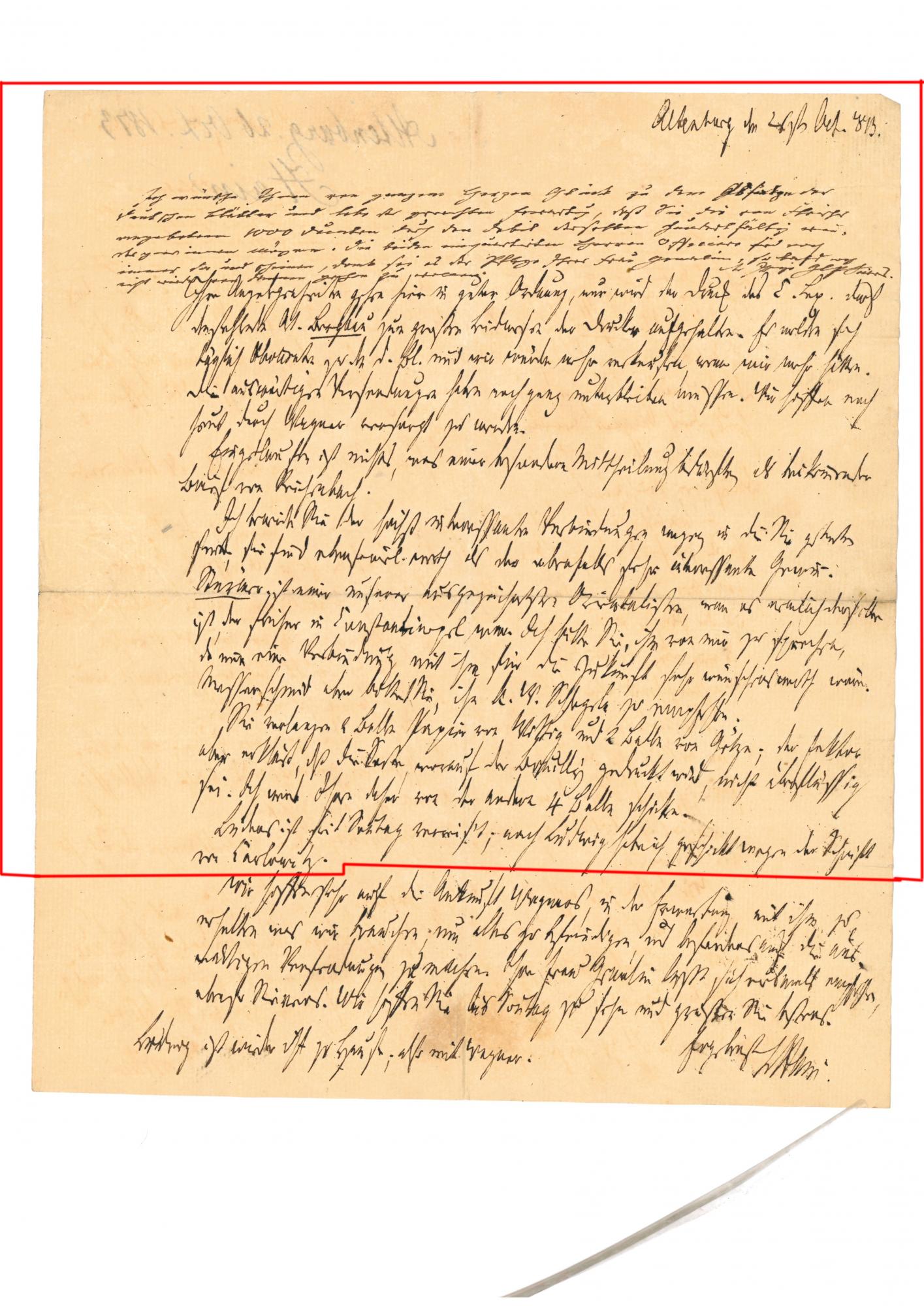
Brief Hain an Brockhaus/ Übersetzung
ich würde gerne diesen Brief transkribieren und komme leider nicht weiter. Den ersten Absatz habe ich schon, allerdings brauche ich nun Hilfe. Vielleicht kann mir einer helfen.
Der Brief ist von 1813 und ist im Anhang.
Hier treiben sich mämlich Leute herum, die allein schon aus Interesse extrem viel Erfahrung mit Kurrentschriften haben, und so was dann locker herunter lesen, während die meisten von uns eher wenig Kontakt zu solchen Dokumenten mit deutlich "ausgeschriebener" Handschrift haben, die sich selbst dnn für außenstehende kaum lesen lässt, wurde lateinische Schreibschrift verwendet.
Wozu brauchst Du denn die Transkription? Scheint ja ein interessantes Projekt zu sein! (Tante Edit ergänzt: Der Dateiname weist darauf hin, dass das Bild für das Hochladen bei Moodle vorgesehen ist, einer Lernplattform für Universitäten, auf der Dozenten Arbeitsaufträge und Informationen bereitstellen können... Irgendwo scheint es an einer Uni ein (Pro-)Seminar zur Edition von Briefen o.ä. zu geben. Doch nicht etwa bei Dr. Strobel, meinem alten Dozenten und Prüfer im Magisterexamen?)
Ja genau es handelt sich um ein Proseminar, wir haben auch schon einige Briefe übersetzt, aber bei dem hier weiß ich leider nicht weiter und kann so gut wir gar nichts entziffern.. Vielen Dank ich schaue dort einmal!
Eigentlich finde ich es ja besser, wenn man sich durch solche Aufgaben durchbeißt: Wenn man einen solchen Text erst einmal bezwungen hat, ist das ein großes Erfolgserlebnis, und man hat auch wirklich was gelernt; das habe ich während meines Studiums oft erfahren dürfen. Die Edition kann Dir natürlich, falls Du Dich irgendwo festgefahren hast, auf die Sprünge helfen und Dir als Schlüssel für schwer lesbare Buchstabenformen dienen. Ich rate Dir aber, sie wirklich nur als Anschub zu benutzen und möglichst viel selbst zu machen. Bei Stockungen wirkt es übrigens meist Wunder, die Arbeit beiseitezulegen und am nächsten Tag noch einmal mit frischem Auge zu betrachten. Transkriptionen brauchen Zeit!
Und Vorsicht: Die Edition ist nicht vollständig und auch nicht ganz buchstabengetreu! Und ich bin mir ziemlich sicher, dass Dein Dozent die Edition kennt und das weiß, so dass ihm auffallen wird, wer abgeschrieben hat, ohne das zu kennzeichnen. Du kannst wahrscheinlich große Pluspunkte sammeln, wenn Du offen darauf hinweist, dass Du die Edition herangezogen hast. Das gebietet natürlich auch die wissenschaftliche Redlichkeit. Die dazu nötigen bibliographischen Angaben zu dem digitalisierten Werk findest Du ganz oben auf der verlinkten Seite.